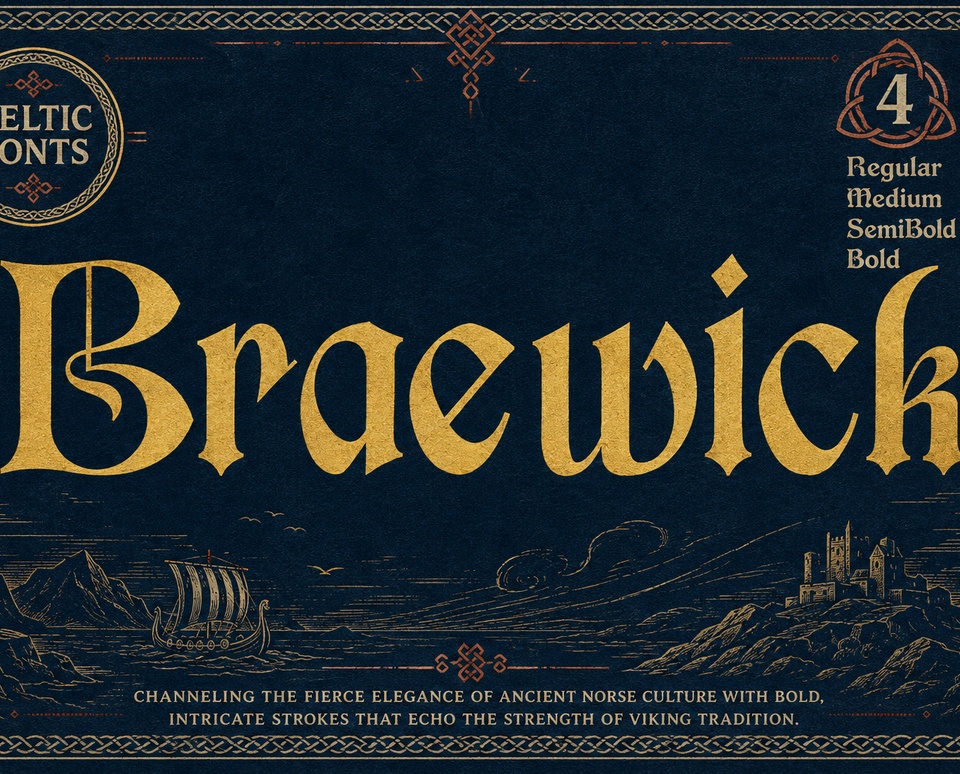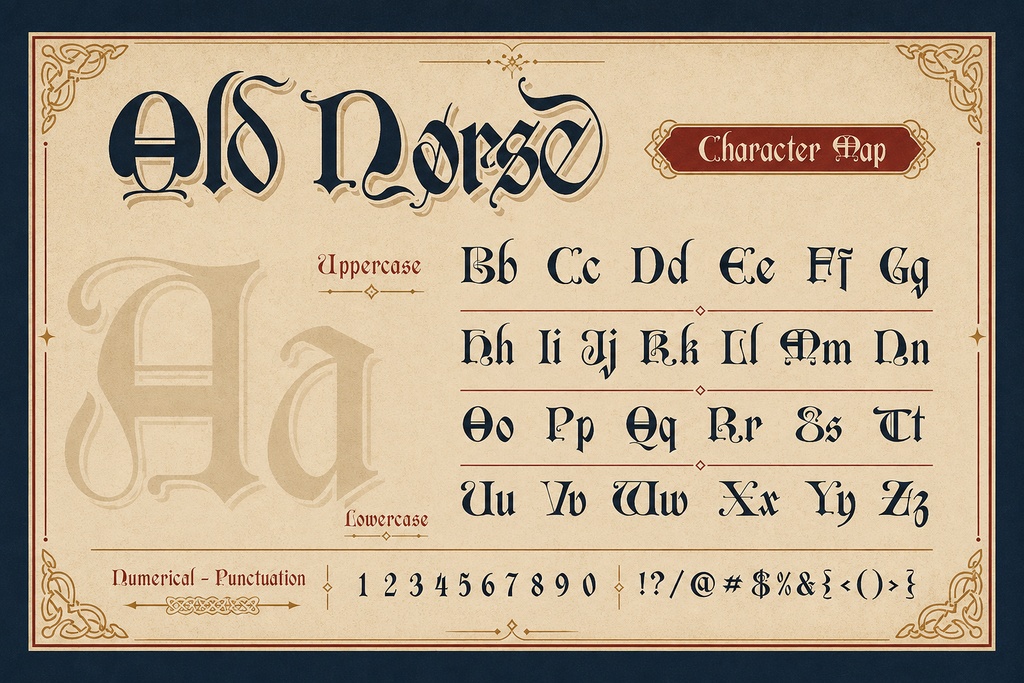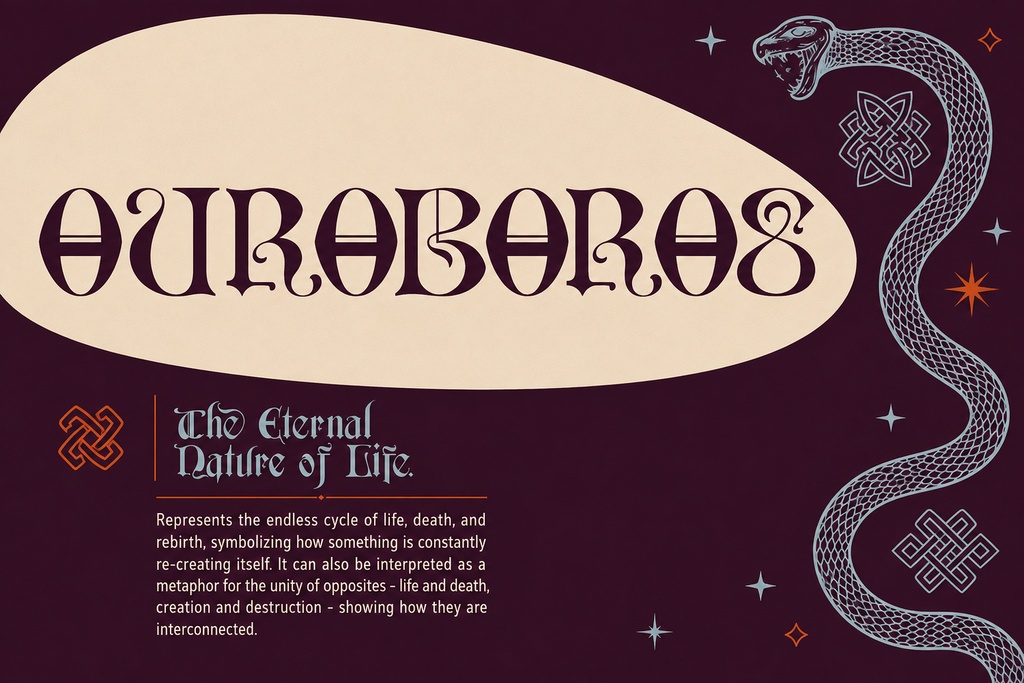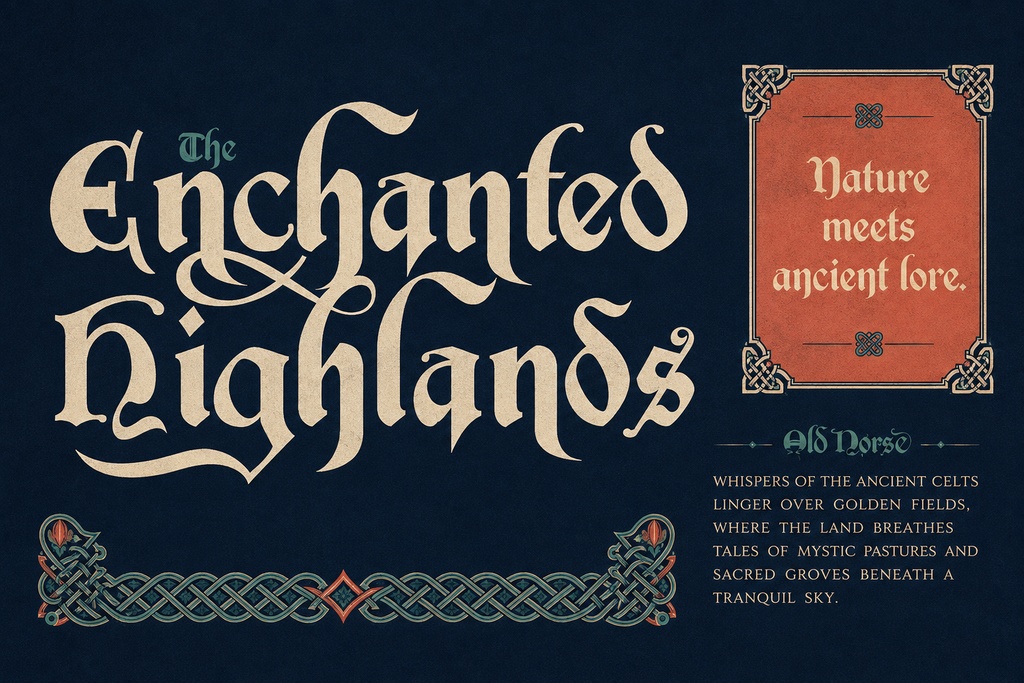
Braewick - ケルト中世ディスプレイフォント
**Braewick**は、荒々しく個性的な雰囲気と、強い歴史的な世界観を持つケルト・中世風のディスプレイフォントです。印象に残るファンタジータイトル、力強い見出し、装飾的なレタリングのためにデザインされており、現代のデザイン制作にも使いやすい実用性を保ちながら、古い時代の碑文のような存在感を文字に与えます。 Braewickは、**Regular、Medium、SemiBold、Bold**の4スタイルで構成されたフォントファミリーです。各スタイルには**380グリフ**が収録されており、表現力豊かなディスプレイタイポグラフィを幅広く楽しめます。大文字・小文字のA-Z、数字、句読点、記号、アクセント付き文字に対応しているため、多言語プロジェクトにも活用できます。OpenTypeのオルタネートやスタイルセットを使用すれば、より個性的な表現を加えることができ、OpenTypeのポジショニング機能とカーニングによって、見出しやロゴの文字間も美しく整えられます。 ### 主な特徴 * 階層や強調表現に柔軟に対応できる4種類のウェイト * 各スタイル380グリフ * 大文字・小文字、数字、句読点、記号、アクセント付き文字に対応 * 装飾的なバリエーションを生み出すOpenTypeオルタネート&スタイルセット * より美しい文字間を実現するOpenTypeポジショニング&カーニング * 各スタイルにOTF、TTF、WOFF、WOFF2ファイルを収録 * 対応するWebプロジェクトで使用できるWebフォント形式 ### 用途 Braewickは、**ファンタジー小説の表紙、歴史をテーマにしたポスター、中世風の見出し**などに最適です。力強いディスプレイデザインは、ゲームタイトル、架空世界のワールドビルディング、RPGブランディング、ロゴ、アパレルグラフィック、Tシャツデザイン、招待状、雑誌表紙、エディトリアルデザイン、パッケージ、装飾テキストなどにも適しています。 複数のウェイトを組み合わせて、印象的なタイトルとサブタイトルを作成したり、オルタネートを使用してロゴ、招待状、ファンタジータイトルに個性的なシグネチャー感を加えたりすることもできます。 ### 対応形式 パッケージには、4つすべてのウェイトについて**OpenType Font(OTF)、TrueType Font(TTF)、WOFF Webフォント、WOFF2 Webフォント**を収録しています。 OTFまたはTTFファイルをコンピューターにインストールすることで、対応するデザイン、イラスト、レイアウト、オフィス、プレゼンテーションソフトウェアで使用できます。WOFFおよびWOFF2は、商用フォントライセンスの規約に従い、対応するWebプロジェクトでご利用ください。 ### ライセンス 商用デザイン制作、クライアントワーク、公開グラフィック、ブランディング、商品、ゲーム、その他の収益を生み出す用途には、**Cubebrush Commercial License**を選択してください。 ライセンスはフォントファイルをデザインリソースとして使用するためのものであり、フォントファイル自体を再配布・再販売したり、単独の商品として公開したりすることは禁止されています。Braewickを商用プロジェクトで使用する前に、購入時に表示されるライセンス内容を確認し、具体的な許可範囲と制限事項をご確認ください。 **Braewickで、次のタイトル、ロゴ、ポスター、ファンタジーブランドに、力強く歴史を感じさせる個性的な存在感を加えましょう。**